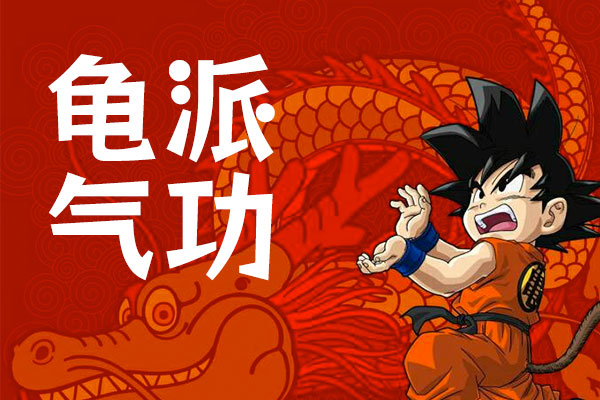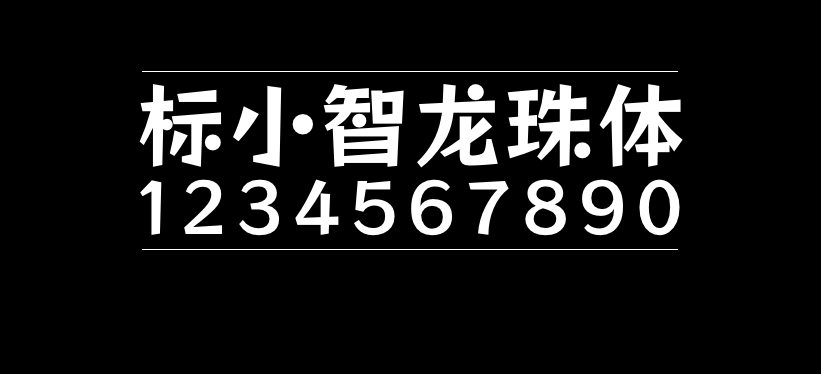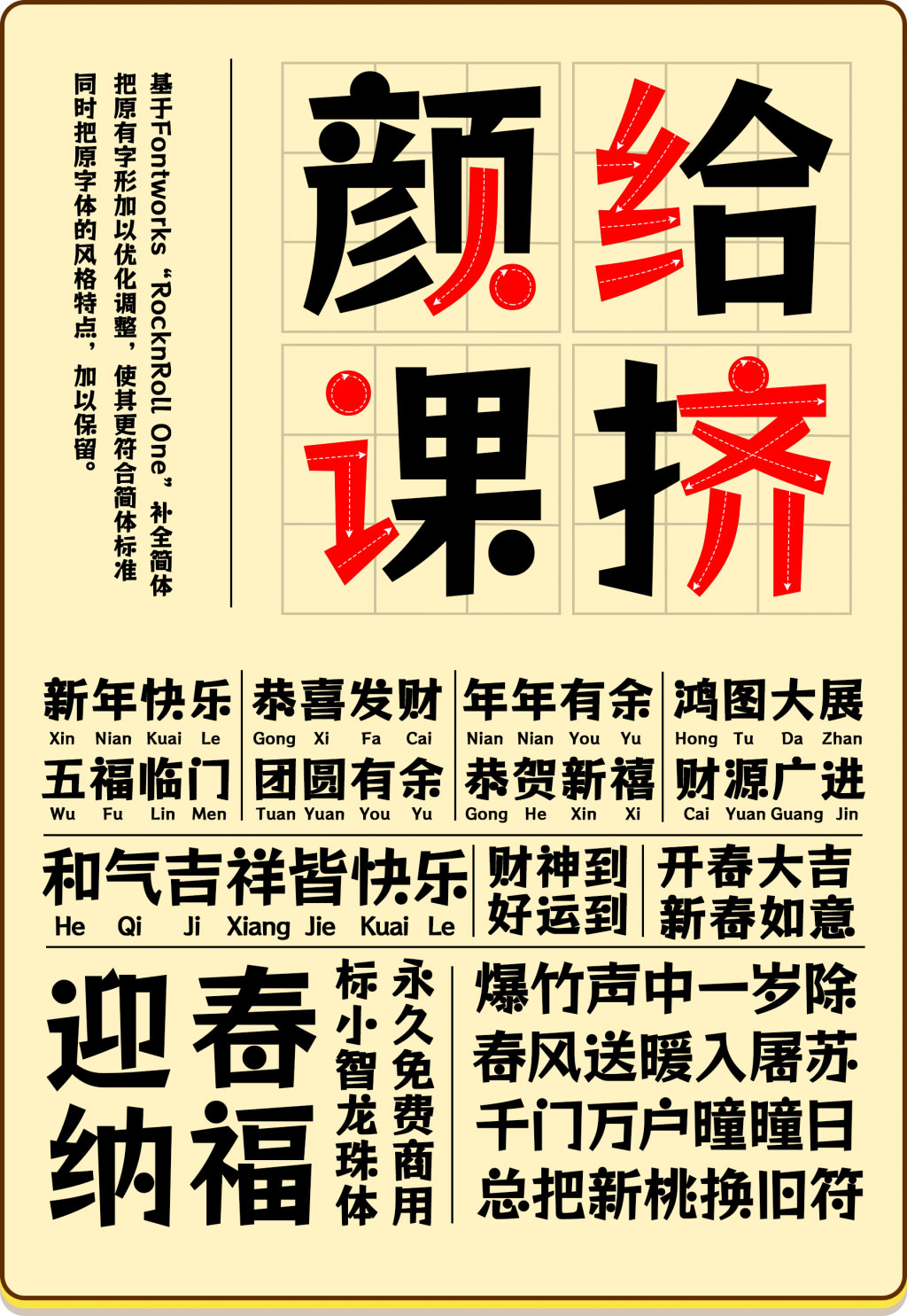
标小智龙珠体
标小智龙珠体是LOGO设计平台标小智基于日本免费开源字体摇滚乐 One(日文名:ロックンロール,出自日本著名字体设计公司Fontworks)字体进行简体字补充的一款字体。
标小智龙珠体力度不同的笔触增加了动量,而圆点则营造出生动活泼的感觉。
标小智龙珠体已覆盖GB2312的6763字,对于繁体的支持度也很好,推荐大家下载使用!